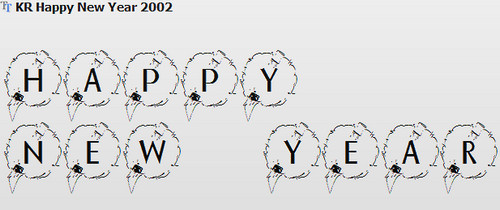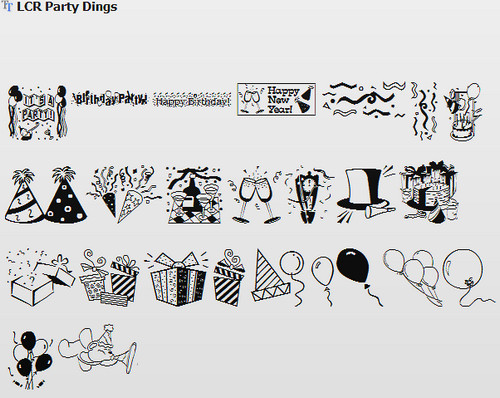
Di solito queste cose un po’ più “leggere” le proponiamo nei week-end, ma il tempo stringe, stringe più che mai. Eccovi allora servita una bella serie di
fonts gratuiti per biglietti, festoni e siti Web che vi aiuteranno a festeggiare il Capodanno 2011, sia nel mondo reale che nel mondo virtuale, nel migliore dei modi.
Per essere precisi, si tratta di 6 set di fonts gratis praticamente perfetti per creare biglietti d’auguri per party di Capodanno, festoni da appendere in casa durante le feste e banner o immagini da inserire in blog, siti personali e forum.
Cocktail Bubbly
Fontdinerdotcom Sparkly
Confetti
KR Happy New Year 2002
NewYearBats – include 52 caratteri diversi per le lettere minuscole e maiuscole (nell’anteprima qui sopra ci sono prima i caratteri maiuscoli e poi quelli minuscoli).
LCR Party Dings – non solo per Capodanno, ma anche per compleanni e altri eventi da festeggiare.